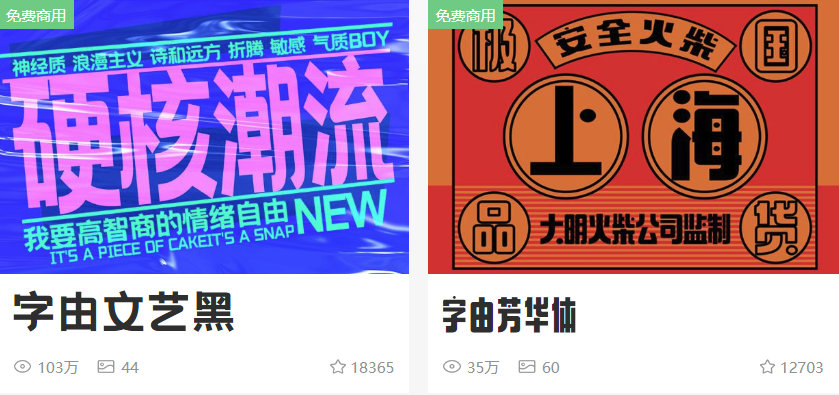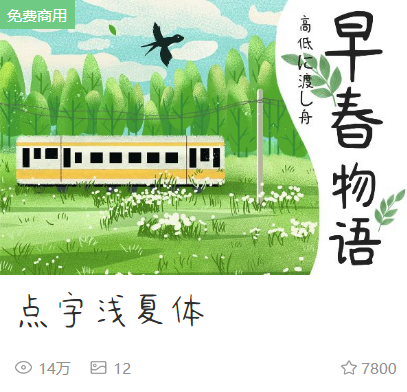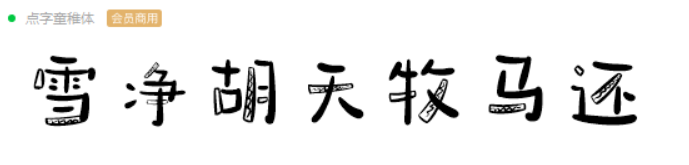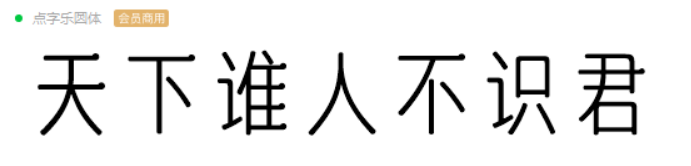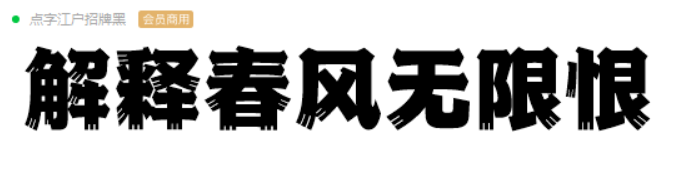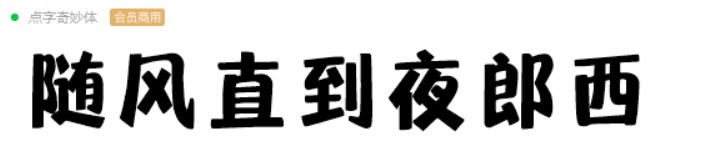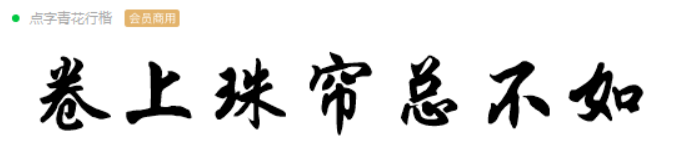
有了这个视频剪辑app,再也不愁用不到字由的字体了
今天柚子又带来了振奋人心的好消息,那就是videoleap上线了字由的9款字体。提起它,做视频的童鞋绝不会陌生,是一款非常强大的剪辑软件。
但它更强大的,是字体的更新,毕竟对视频剪辑来说,字体是仅次于音频的重要存在,同意的举手!
柚子也是刚接触剪辑app不久,发现上手真的很快,唯一的不足就是可选字体少,无法最准确地表达情绪,不过好在videoleap出现了,只要打开你的苹果手机(没有的也不用担心,后面会讲),就会发现新大陆……
此次上线的既有我们的免费好CP——字由文艺黑、字由芳华体。
也有日式小清新的点字浅夏体。
会员商用部分,则是点字库人气担当的6款字体。
用在videoleap上是什么样呢?没有苹果手机的柚子,用ipad整了一个hhh~
再加上视频素材康康,很有感觉对不对?
当然它还有很多特效,等待你去一一探索,比如做个透明镂空字体,加上音效更炫酷(视频在字由视频号上)!
最重要的是,以前用户心心念念想在手机上或者ipad上用到字由的字体,这次通过videoleap,终于梦想成真!